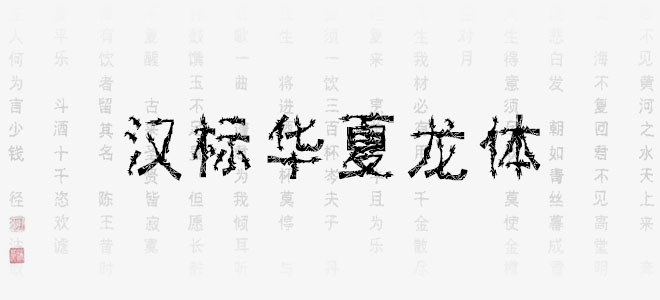
漢標(biāo)華夏龍?bào)w由漢標(biāo)字庫(kù)出品的藝術(shù)字體,筆觸粗細(xì)適中,字形端正大氣,具有很好的視覺感,適合應(yīng)用于藝術(shù)設(shè)計(jì)、平面宣傳設(shè)計(jì)、網(wǎng)頁設(shè)計(jì),書法字帖等領(lǐng)域,喜歡的朋友快來下載使用吧!
漢標(biāo)華夏龍?bào)w